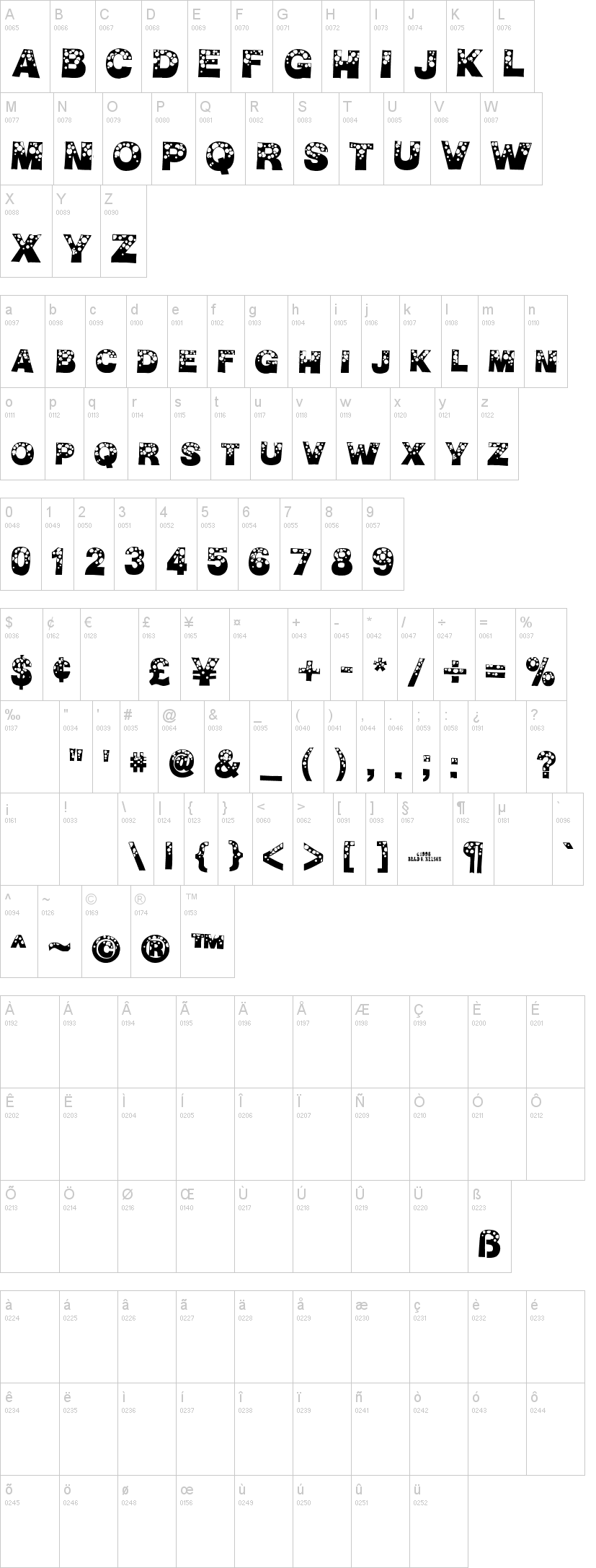
BubbleMan 字体是一种充满趣味性的字体,其特点是字母和数字看起来像是水泡或气泡。这种字体常用于设计海报、广告、宣传册和其他需要吸引眼球的场合。 BubbleMan 字体有许多不同的变体和风格,包括粗体、斜体、阴影和荧光颜色等。这使得设计师和艺术家可以根据需要选择最适合的字体风格。 虽然 BubbleMan 字体非常适合用于儿童相关的设计,但它也可以用于其他类型的设计。无论是在海报、标志还是设计布局,BubbleMan 字体都能为设计增添活力和趣味性。内容介绍
BubbleMan是一款非常不错的手写艺术字体,具有很好的视觉感,适合于文化类的宣传设计、商业类品牌的广告和产品包装设计以及个性化文字排版等较多场景。